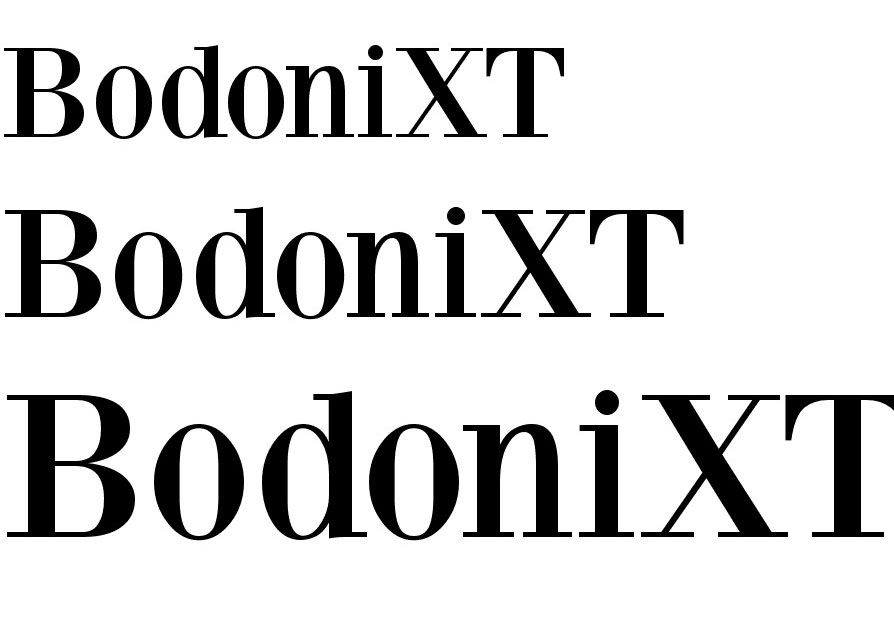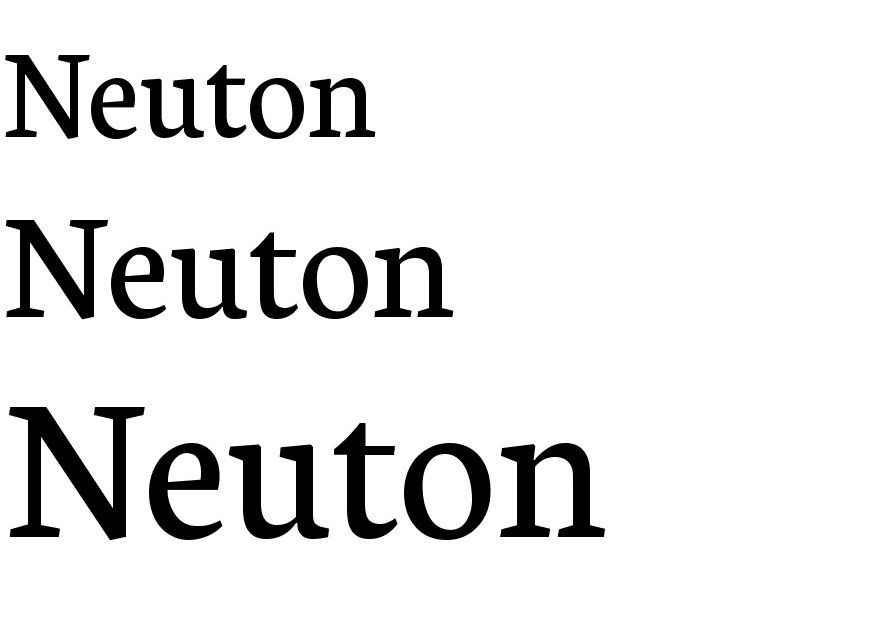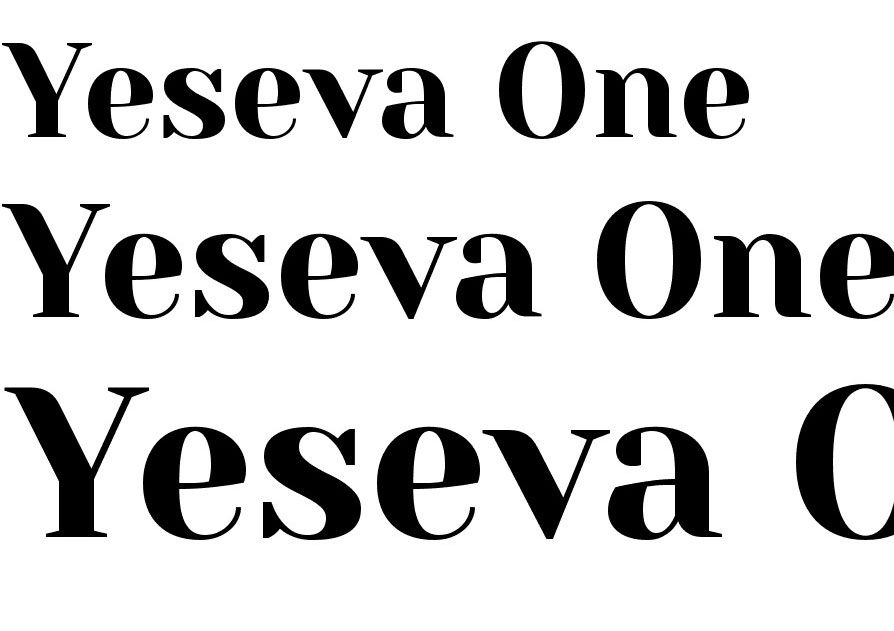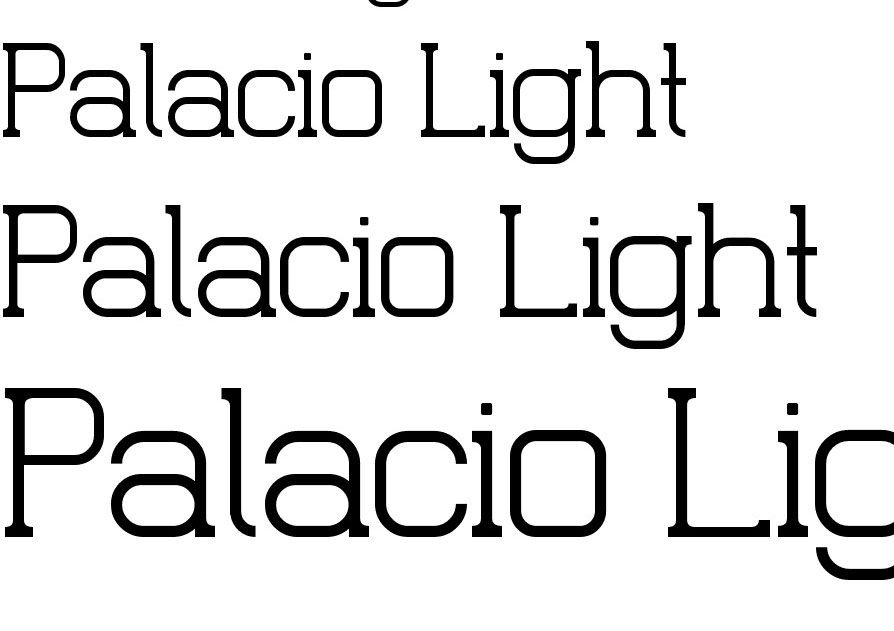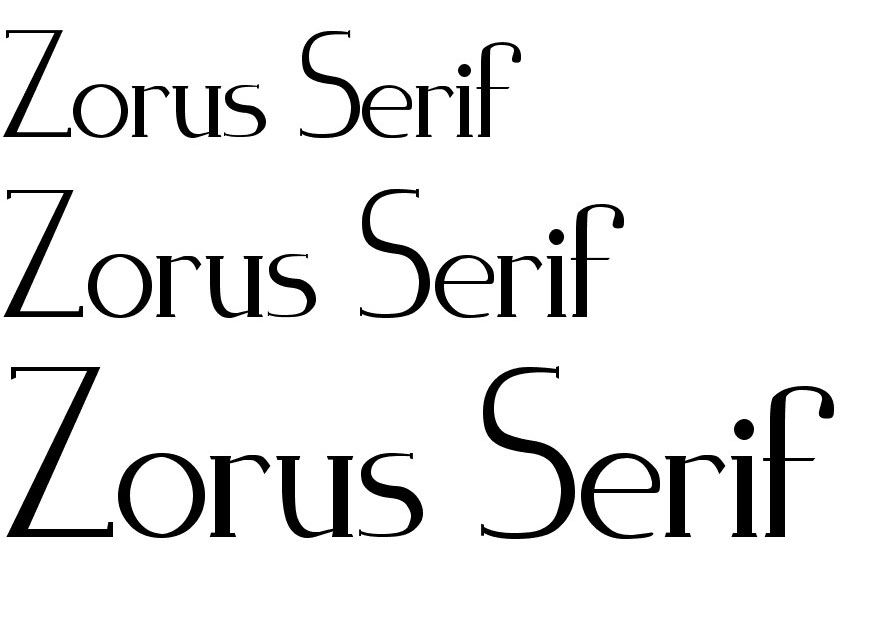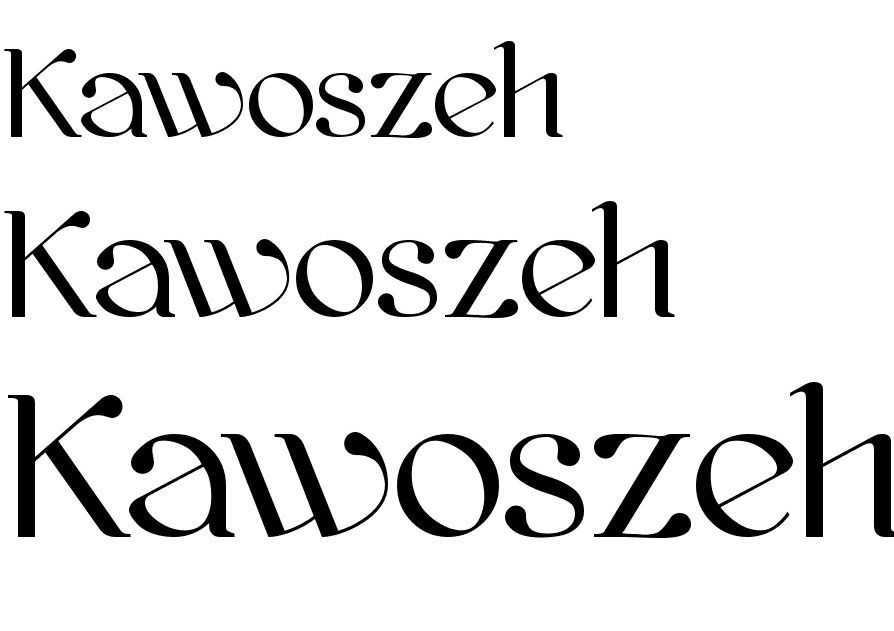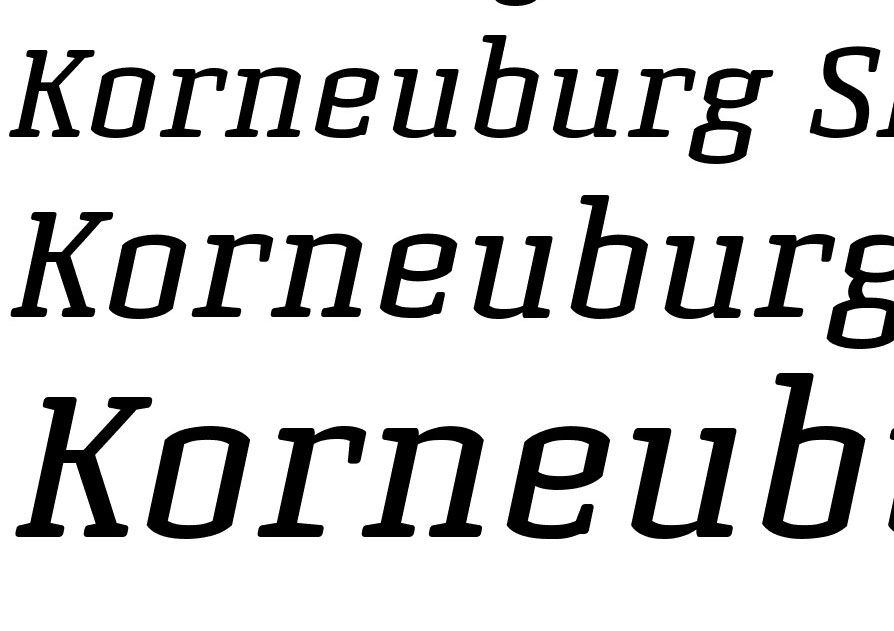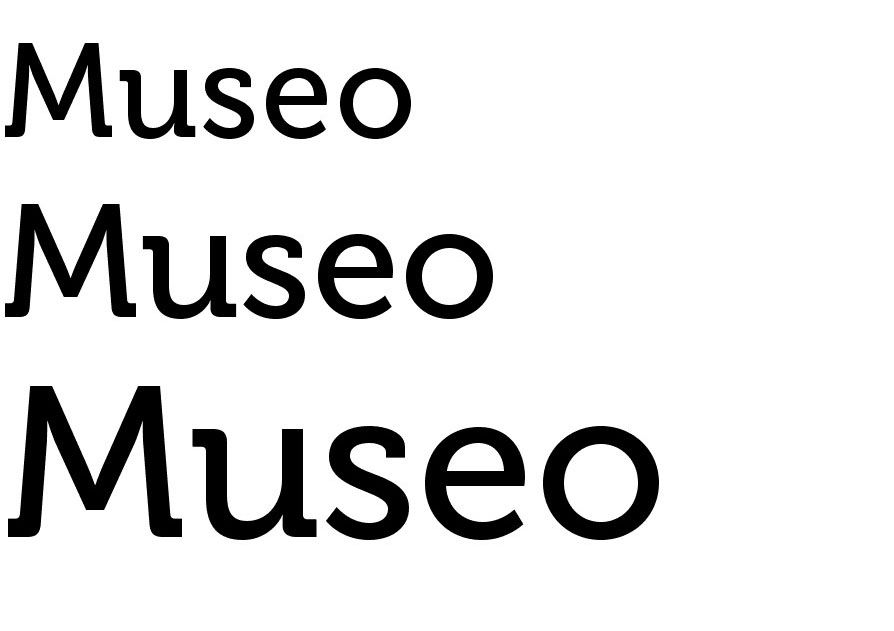
Más de 15 fuentes Serif gratuitas para usar en su trabajo
Una de las primeras decisiones que se deben tomar al seleccionar un tipo de letra para el texto, y una de las más importantes, es si elegir serif o sans serif. Esta determinación no debe ser arbitraria. Debe basarse en varios puntos clave con respecto al proyecto en cuestión. Sin embargo, una vez que se toma esta determinación, su búsqueda de tipografía debería comenzar a reducirse significativamente.
Si bien la mayoría de la gente puede considerar que las serifas son puramente decorativas, tienen un propósito útil. Al menos a los ojos de algunos.
Una escuela de pensamiento es que los tipos de letra serif aumentan la legibilidad y la velocidad de lectura de pasajes largos de texto. Se dice que las serifas ayudan al ojo a viajar a través de una línea y, por lo tanto, evitan fallas de concentración en pasajes largos de texto.
La otra escuela de pensamiento es que leemos mejor lo que más leemos, y lo que vemos en la mayoría de los pasajes largos de texto son tipos de letra serif. El tipo de letra serif ha sido dominante en revistas, libros y periódicos durante muchos años.
Dominio, o popularidad para el caso, no debe necesariamente equipararse con legibilidad. Muchos tipos de letra sans serif son más legibles en un tamaño dado que muchos diseños serif. Esto parece ser particularmente cierto en la web, especialmente en sistemas de baja resolución o en pantallas pequeñas.
Independientemente del estilo que elija, preste mucha atención a las características particulares del diseño de una fuente y cómo se relaciona con la legibilidad y la legibilidad, y hágalo tanto para romana como para cursiva.
Mientras explora estos 15 ejemplos, no hay duda de que elegiría algunos basándose únicamente en el estilo, mientras que otras opciones pueden depender más del escenario en el que aparecerá la fuente, y probablemente sea la mejor opción. De cualquier manera, eligiendo fuentes gratis como estos significarán más dinero en su bolsillo.
Fuente Coldiac Luxury
Diseñada para lucir elegante en tamaños pequeños o grandes, esta fuente GRATUITA tiene que ver con profesionalismo, gracia y versatilidad.
Neuton
Esta fuente serif limpia y oscura recuerda algo a Times New Roman. Es, hasta cierto punto, de inspiración holandesa, con su gran altura, extensores cortos y ancho compacto. Neuton es una buena opción para el uso de pantallas, donde la economía de espacio suele ser un factor importante.
Servidor uno
Yeseva One es atrevida, pero sin embargo muy femenina. Esta fuente única parece fluir de una letra a otra. El nombre es un despegue de 'Yes Eva'; y podría tomarse como un signo de total acuerdo entre un hombre y una mujer.
Palacio Light
Las fuentes Homestead y Museo proporcionaron la inspiración para Palacio. Esta fuente muy simple, diseñada por Nathan Thomson, es más notable por sus líneas finas y elegantes.
Zorus Serif
Zorus Serif habla de antaño. Llena de encanto y elegancia, esta fuente fue diseñada por Jérémie Dupuis.
Kawoszeh
Las fuentes GLUK diseñaron esta fuente tradicional con sus exquisitos trazos de letra.
Korneuburg
La ciudad de Korneuburg en la Baja Austria fue la inspiración para esta obra maestra atrevida y peculiar. Fue diseñado por Flö Rastbichler y será una gran fuente de párrafo.
Museo
Museo es una familia de fuentes semi-slab. Fue diseñado por Jos Buivenga, quien se dice que se inspiró en la letra U mayúscula.
Uso
Como se señaló anteriormente, los libros y periódicos, así como la mayoría de las revistas, utilizan tipos de letra serif, en parte por un precedente histórico y en parte por consideraciones de legibilidad. Es más probable que los tipos de letra sans serif se encuentren en folletos, volantes e informes anuales. Algunas revistas utilizan el tipo sans serif como medio para establecer su marca.
Sans serif se usa cada vez más en títulos, leyendas, cuadros y gráficos, a pesar de que el tipo de letra serif se usa en el cuerpo del texto. Sans serif tiene una ventaja distintiva sobre serif; las formas de las letras tienden a simplificarse y tienden a evitarse los problemas de legibilidad causados por las serifas para tamaños muy pequeños.
Audiencia
La audiencia puede ser importante al seleccionar un tipo de letra. Sans serif suele ser una mejor opción para los niños y los lectores principiantes, ya que las formas de letras simplificadas son más reconocibles. Lo mismo puede ser cierto para las personas que tienen ciertas discapacidades visuales (las letras mayúsculas gruesas pueden ser las mejores, por ejemplo). La audiencia probable de lo que publica, ya sea en forma impresa o en la web, debe tenerse en cuenta al decidir el tipo de letra principal que planea usar.
Fuentes Serif adicionales que puede encontrar de interés
Magnífico
BodoniXT
Gabriel Serif
Napoleodoni Bold
Providencia
Novello Pro
ParmaPetit Normal
Corresponsal